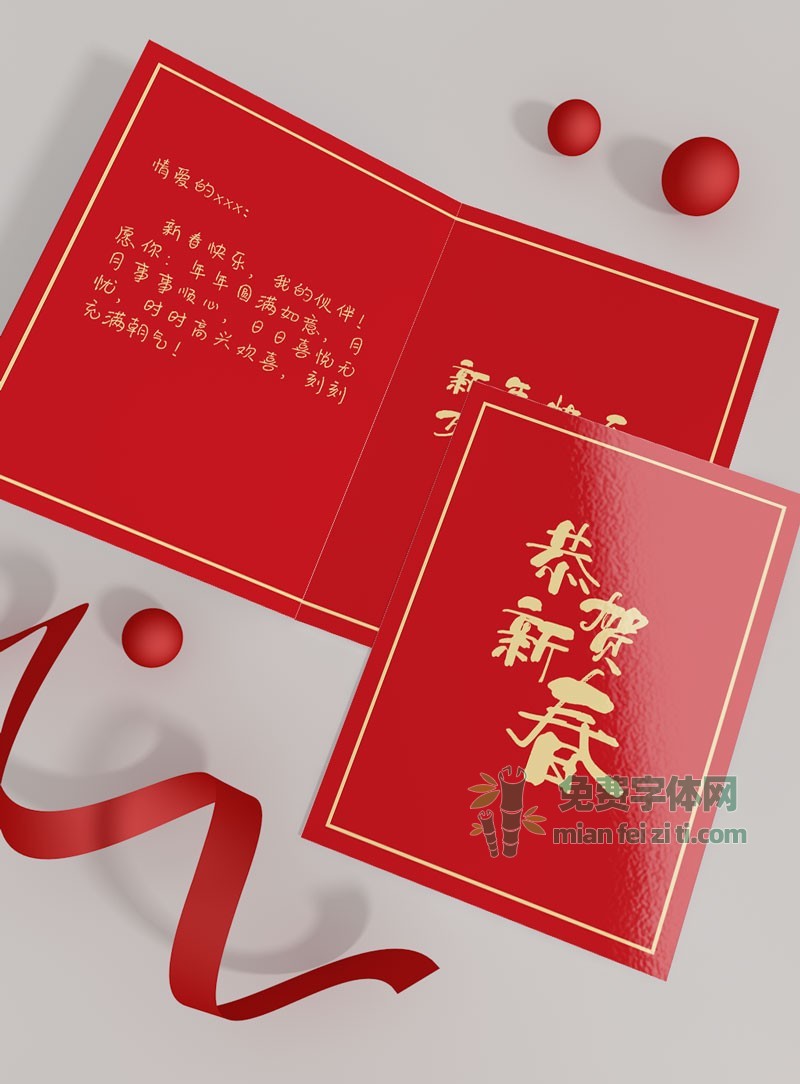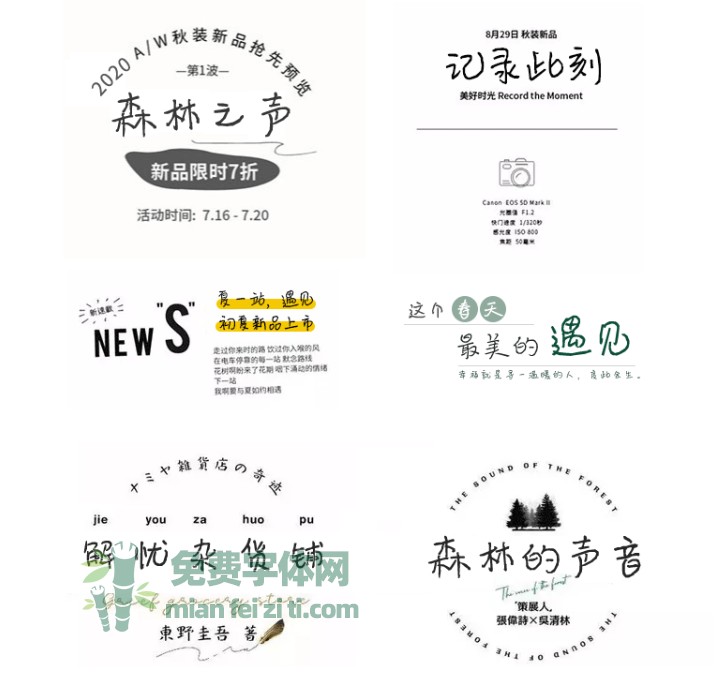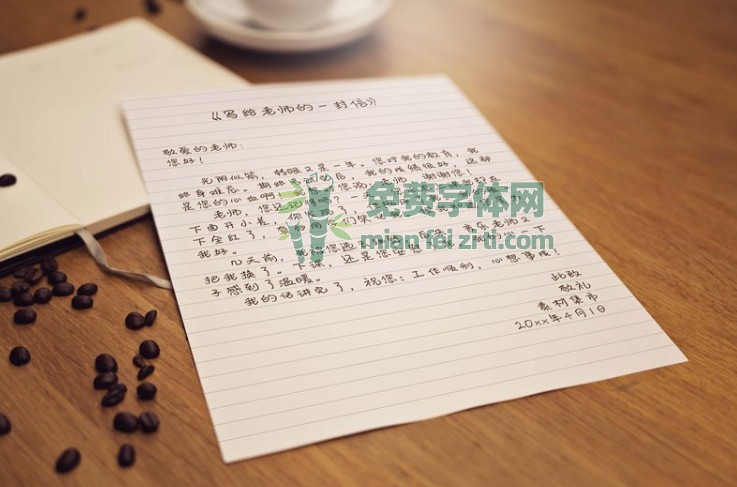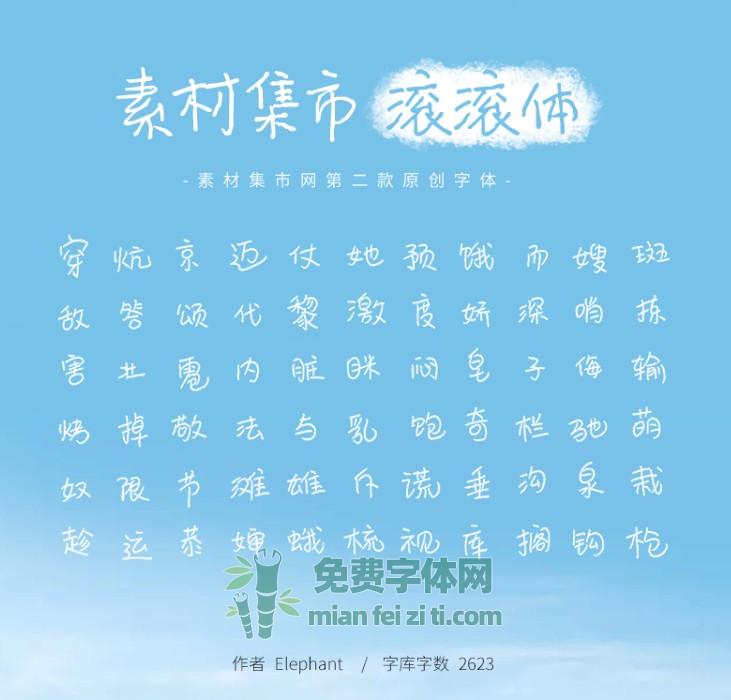
素材集市「滚滚体」欣赏预览字体资讯
「滚滚体」是素材集市第二款原创字体,字体手稿是设计师 Elephant 独立完成,由素材集市打包生成字体,共 2623 个汉字和字符,因为是纯手写,所以每个字体都是独一无二,很随性,真实还原手写字体效果。
字体简介
字型圆滑可爱,笔画随性俏皮,所以命名「滚滚体」,适合用在手帐字体、日签、书信等书写使用。
应用场景
书信字体效果极佳(如:请假条/离职申请等)
新年/生日贺卡祝福文字